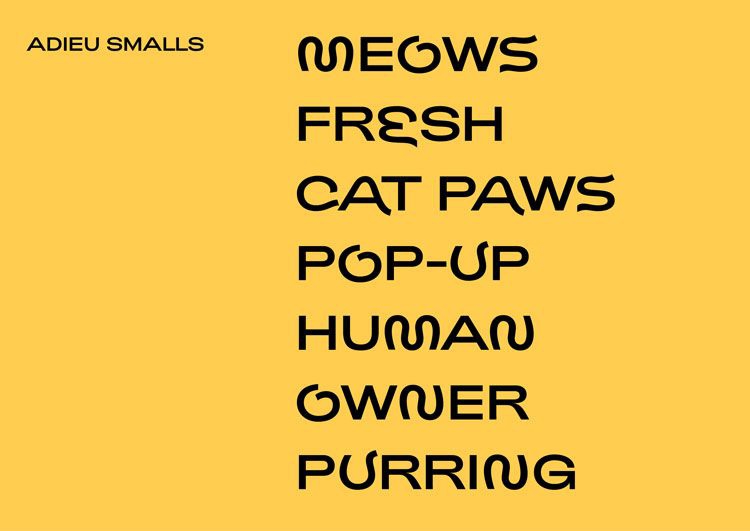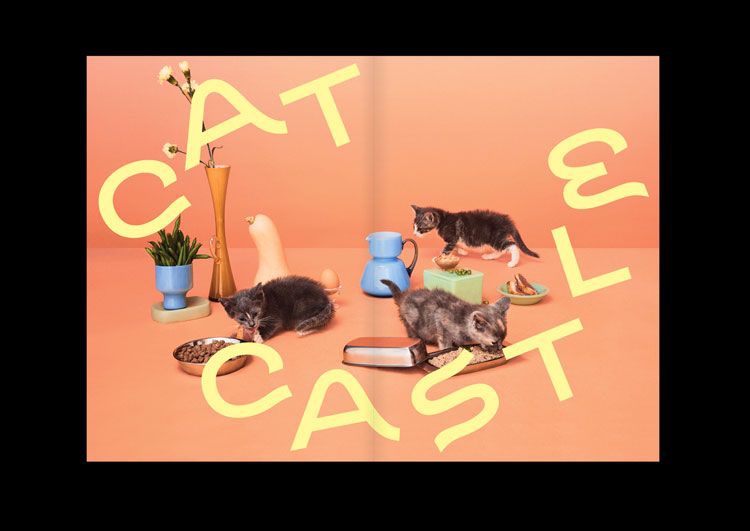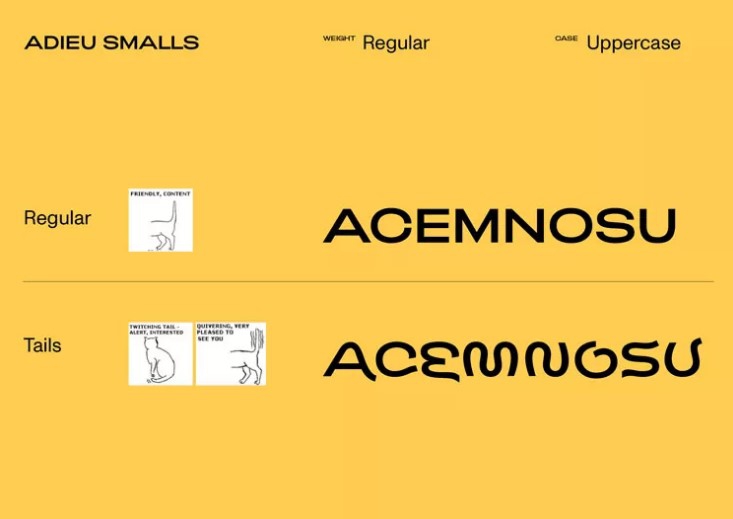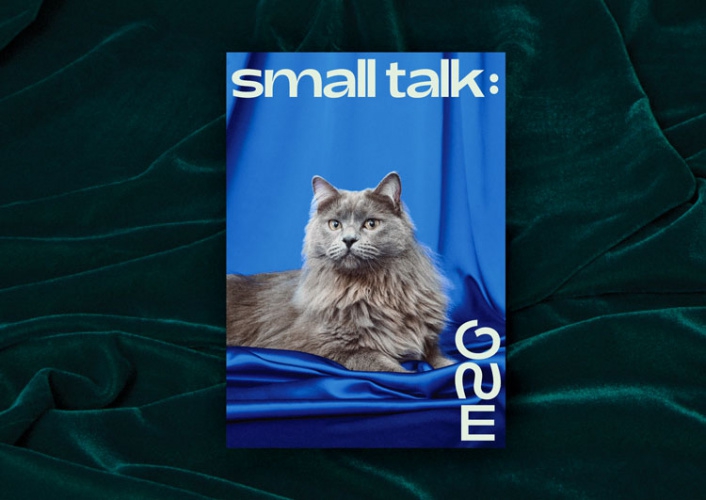
Бренды любят создавать собственные шрифты для использования в своей айдентике. Производитель кошачьей еды Smalls не стал исключением и заключил контракт с агентством Good Type в Осло, чтобы создать шрифт Adieu Smalls.
Новый шрифт основан на уже имеющемся Adieu (тоже от Good Type). Для его преобразования дизайнеры черпали вдохновение… из кошачьих хвостов. Команда креаторов наблюдала за тем, как кошки могут скручивать свои хвосты в различных ситуациях, а затем использовала эти образы в начертаниях букв.
«Кошачий» шрифт можно увидеть на сайте бренда, на упаковке и в свежем номере журнала Small Talk, который станет частью рекламной кампании бренда.
Создатели шрифта отмечают, что кошки вдохновляют дизайнеров далеко не впервые. Однако обычно «кошачьи» шрифты основываются на изгибах тела, а не хвоста. Дизайнеры также обращают внимание на эстетичность новой типографики.
В данном исполнении шрифт скорее является дополнением к основным визуальным образам — кошкам. В отрыве от контекста я бы не сразу догадался, что это кошачьи хвосты. С изображениями кошек он «работает» значительно лучше. Кроме того, по всей видимости, стилизации подверглись не все литеры шрифта, что не позволяет использовать весь потенциал адаптации в тех словах, которые содержат исключительно не стилизованные буквы.
Использование «бронированных» шрифтов продолжает оставаться наглядным примером того, что коммуникации бренда выходят за стандартные рамки визуальных коммуникаций. «Стандартных» визуальных точек контакта, свободных от конкурентов, становится всё меньше, поэтому шрифт начинает выполнять роль дополнительного якоря в передаче смыслов. В таком случае шрифт перестаёт быть исключительно носителем вербальных смыслов и наполняется семиотикой, передающей более глубокие уровни коммуникаций бренда: его характер, направленность, и даже становится рабочим инструментом в борьбе за отдельные психографические и поведенческие сегменты аудитории. Помимо всего прочего, собственный шрифт по-настоящему бесценен в качестве инструмента создания атрибуции с брендом в рекламных кампаниях, тем самым он позволяет увеличить эффективный охват не только за счет визуальной, но и типографической составляющей коммуникации.
На мой взгляд, единство концепции и ее исполнения — просто обязательно. И очень круто, что таких примеров становится больше. Радует, что бренд-менеджеры понимают и принимают такой креатив вместо того, чтобы: «Почему это у вас тут корявый шрифт, исправьте на «нормальный!».
Качественная концепция всегда должна раскрываться подобно цветку в сознании потребителя и коммуницировать на всех возможных уровнях, по-разному донося идею своего проекта. Гораздо хуже, когда все в концепции — вижуал, слоган, шрифт и пр. — из разных областей. В таком случае цельного представления и образа просто не складывается. Становится невозможно ответить на вопрос: «О чем этот бренд?». И кстати этим же вопросом («О чем этот бренд / о чем этот проект?») советую всегда проверять свои проекты. Если ответ начинает размываться и усложняться — значит работа сделана неубедительно.
Так что ребята-мегамолодцы, красавчики!
Иметь собственный шрифт — это редкость для брендов. Это сильный визуальный инструмент, который прямо и открыто коммуницирует с потребителем. Также здорово, что создатели бренда выбрали такой нетривиальный путь, решили копнуть глубже в особенности поведения питомца, а не брать классические кошачьи мордочки.
Дружелюбный и игривый характер бренда удалось отобразить при помощи шрифта. С моей точки зрения, скругление окончаний букв доиграло бы историю про хвосты.